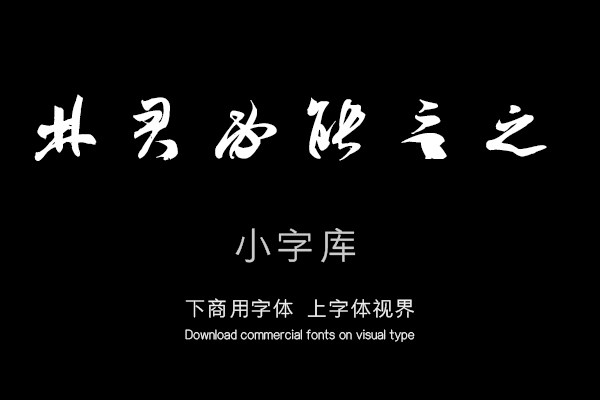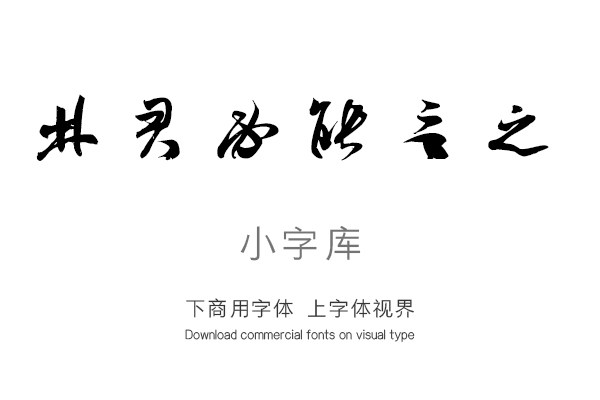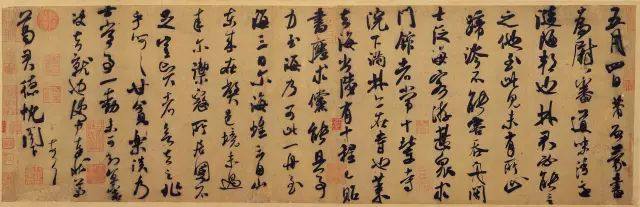
《汉标米芾德忱帖》是一款根据北宋米芾《德忱帖》,经过再次调整制作的小字库,该小字库共收录了该真迹作品中约191个字体。单字授权
五月四日,芾启:蒙书为尉,审道味清适。涟,陋邦也,林君必能言之。他至此,见未有所止,蹄涔不能容吞舟。闽士泛海,客游甚众,求门馆者常十辈,寺院下满,林亦在寺也。莱去海出陆有十程,已贻书应求,倘能具事,力至海乃可,此一舟至海三日尔。海鳇云自山东来,在弊邑境未过来尔。御寇所居,国不足,岂贤者欲去之兆乎?呵呵!甘贫乐淡,乃士常事,一动未可知,宜审决去就也。便中奉状。芾顿首。葛君德忱阁下。